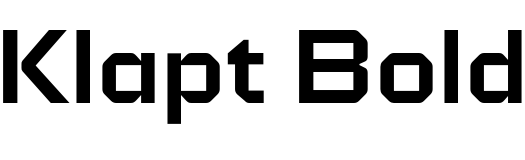
Сімейство: Klapt (4 шрифта)
Асоціації зі шрифтом Klapt BoldОсобистість і характер шрифта:
рівний, квадратний, точний, логічний, холодний, автоматичний, техногенний, твердий, статичний, різкий, чіткий, стійкий, стабільний, прямокутний, міський, сучасний, машинний, інженерний, урбаністичний, креслярський, Простий, надійний, впевнений, сталевий, космічний, переконливий, серйозний, сильний, індустріальний, залізний, мужній, військовий, армійський, промисловий, спортивний, залізничний, футуристичний, робочий, кінематографічний, гранчастий, ігровий, рубаний
конструктор, креслення, архітектура, інженер, автоматика, урбаністика, дизайн, Місто, електроніка, авто, інструмент, робот, гра, космос, промисловість, війна, армія, зброя, завод, металургія, верстат, тара, склад, порт, ящик, патрони, техніка, прилад, ремонт, депо, шолом, уніформа, вагон, авіація, літак, автомат, шутер, екшен, спорт, машинобудування, охорона, захист, паливо, транспорт, страйкбол, поліція, будівництво, взуття, цегла, автобус, технології, андроїд, залізо, фантастика, коворкінг, залізниця, робочий, рентген, кіно, кубики, лего, кіберспорт, комп'ютерна гра, вантаж, вантажоперевезення, вантажівка Шрифт має ознаки стилів: